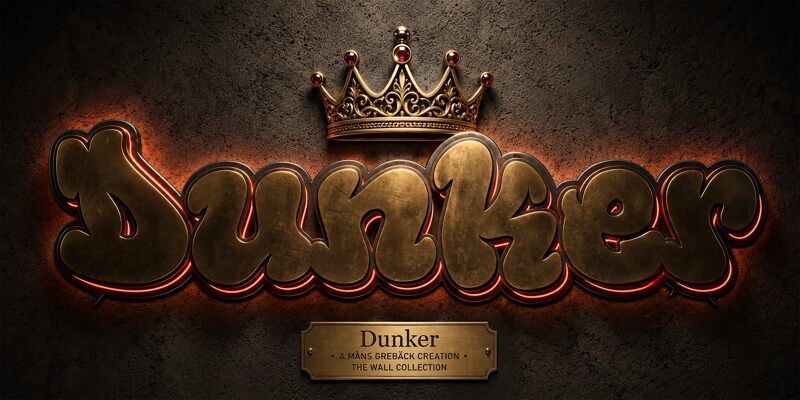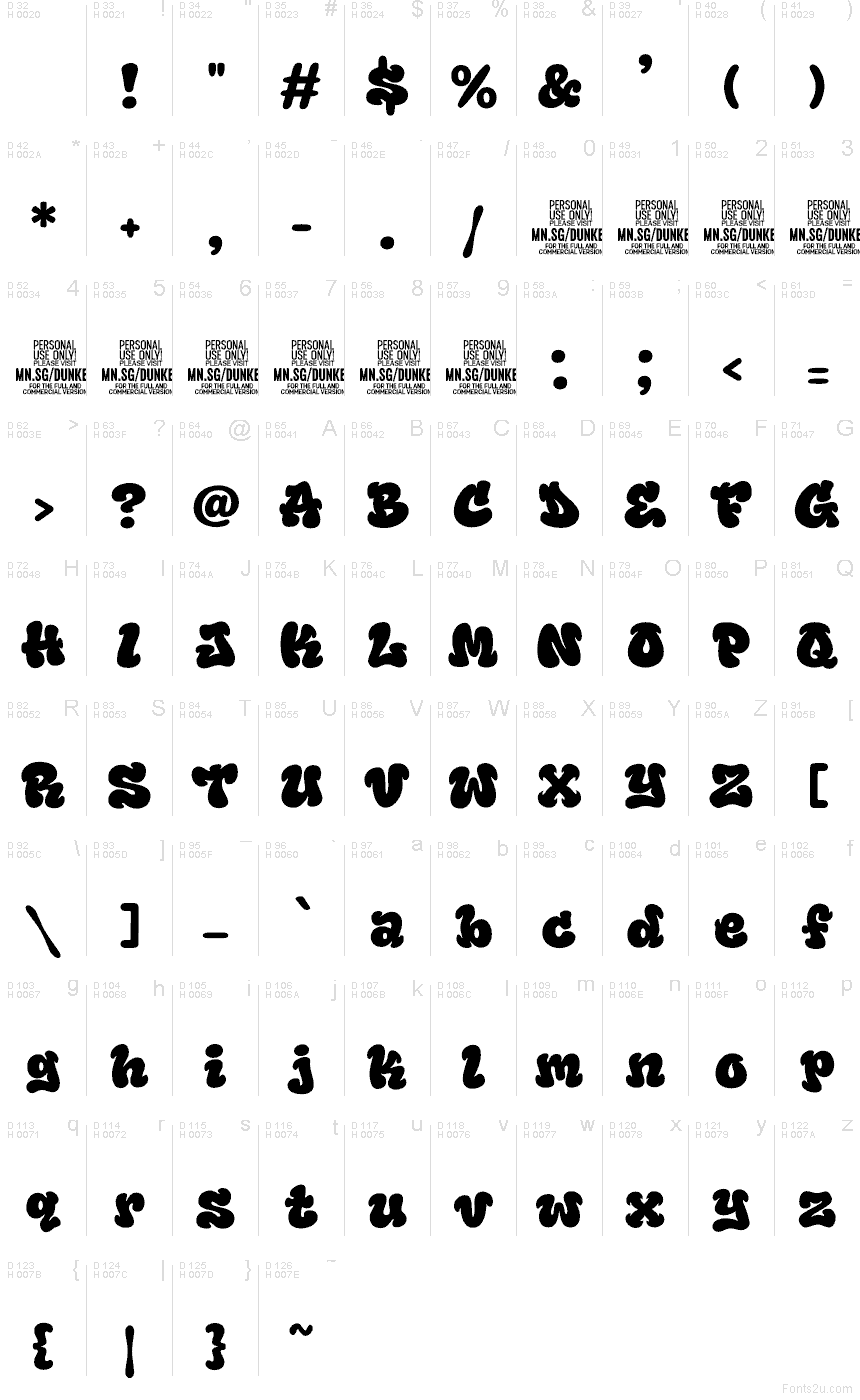
Dunker de Mans Greback AB é uma fonte de display gratuita com letras volumosas e de cantos suaves, com um forte toque dos anos 1970. Traços grossos curvam-se em formas vivas e irregulares, com uniões comprimidas e extremidades enroladas que dão às letras um aspeto desenhado à mão, em vez de mecânico.
Capas de álbuns são um bom lugar para ela, e essas mesmas formas fluidas adequam-se a cartazes de festivais, grafismos de streetwear e embalagens de alimentos divertidas. Aqui, as letras podem tornar-se um emblema ilustrado em vez de texto comum.